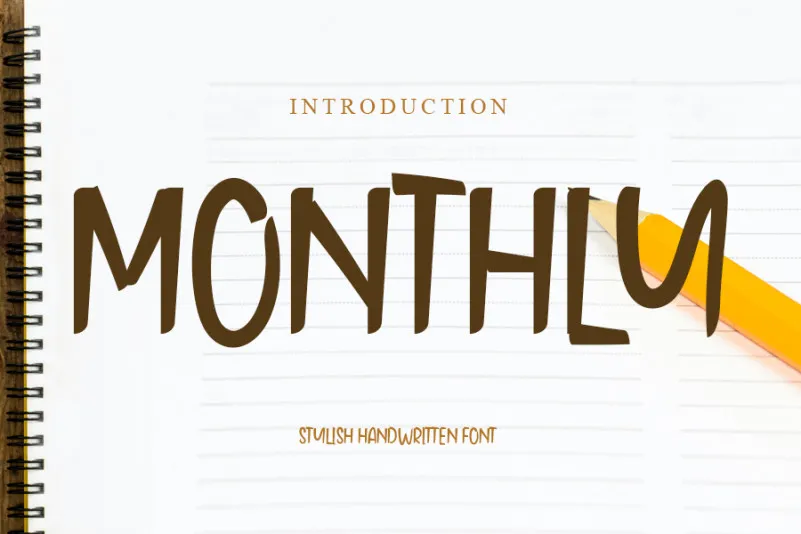
Monthly Display Font – Download Grátis
A “Monthly Display Font” é uma elegante fonte escrita a mão que oferece um toque amigável e simples. Perfeita para uso em diversas aplicações, como logomarks, convites, títulos de página principal, roupas personalizadas, cabeçalhos de documentos ou rótulos, ela também é perfeita para o design de adesivos, notícias, postais, cartões de convidado e até mesmo em estandards. Seja você uma marca querendo um visual agradável e sofisticado, uma empresa buscando unir estilo e funcionalidade ao criar materiais promocionais ou até mesmo alguém que adora usar sua criatividade na moda e no design de roupas, esta fonte está aqui para te ajudar. Com “Monthly Display Font”, o design pode ser tanto informativo quanto agradável aos olhos.
Designer: freshtypeink